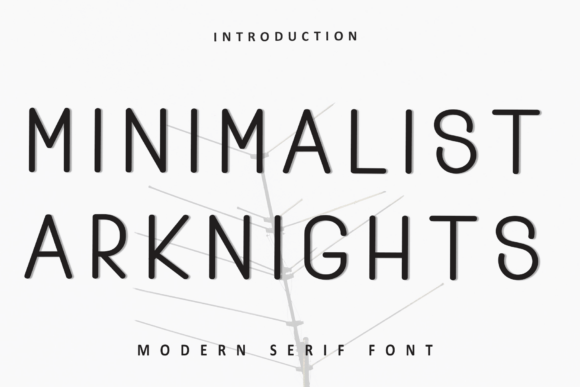
Minimalist Arknights
หากคุณกำลังมองหาเนื้อหาคุณภาพสูงเช่น Minimalist Arknights แพ็คเกจพรีเมียมนี้เป็นตัวเลือกที่ยอดเยี่ยมสำหรับโปรเจ็กต์สร้างสรรค์ของคุณ
ไม่ว่าคุณจะสร้างผลิตภัณฑ์ POD (Print on Demand) คำเชิญงานแต่งงาน หรือกราฟิกโซเชียลมีเดีย Minimalist Arknights ก็เหมาะสมอย่างยิ่ง